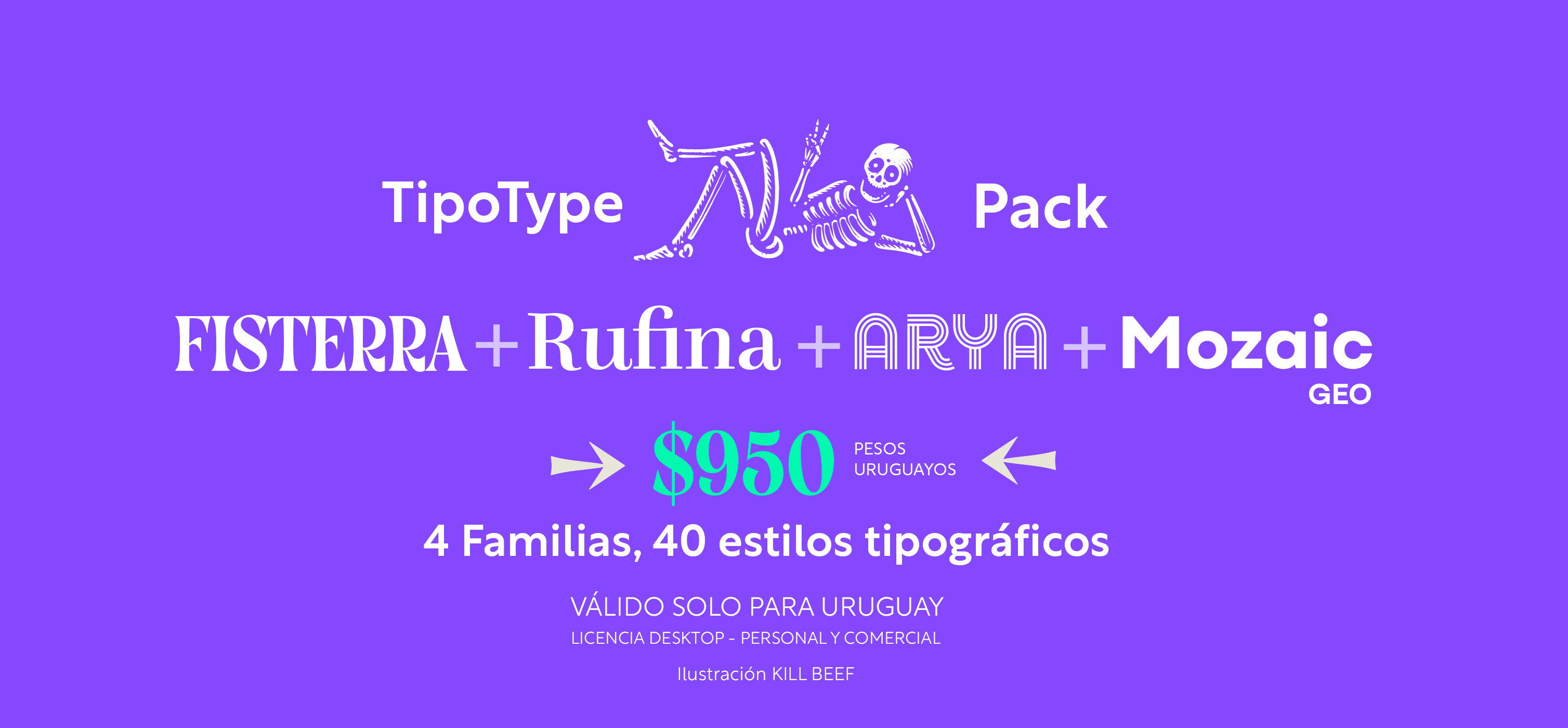
Promo Pack
— 40 estilos
Arya family
Estas cuatro familias tipográficas cubren un amplio margen de estilos gráficos, son un buen repertorio de tipografía uruguaya con el que resolver varias y distintas situaciones de comunicación.
Mozaic es suma, su identidad se enriquece con aportes provenientes de distintas tradiciones para formar una sans moderna que incluye una cobertura idiomática muy completa para una amplia variedad de familias de lenguas basadas en el alfabeto latino.
Fisterra, con sus variantes Morte y Fisterra, ofrece la dualidad entre la calma y la intensidad. Informal y serif. Morte tiene la suavidad y el humanismo de sus curvas; Fora, la precisión y exactitud de sus ángulos agudos.
Rufina es la elegancia hecha tipografía (no en vano es la elegida por la casa real de Reino Unido para su sitio web oficial (https://www.royal.uk/) sencillez, delicadeza y elegancia son las palabras que mejor la caracterizan. Seduce al espectador de una manera sutil y elegante. Mezcla de formas contrastantes influenciadas por Bodoni con el toque emotivo de la pluma del calígrafo.
Arya es robusta y distintiva para títulos o textos destacados, es un tipo de letra simple y sencillo, basado en proporciones romanas. Se pueden combinar en capas. Las versiones cápsula (Blanco y Negro) están diseñadas para realizar etiquetas de forma rápida, sencilla y elegante.